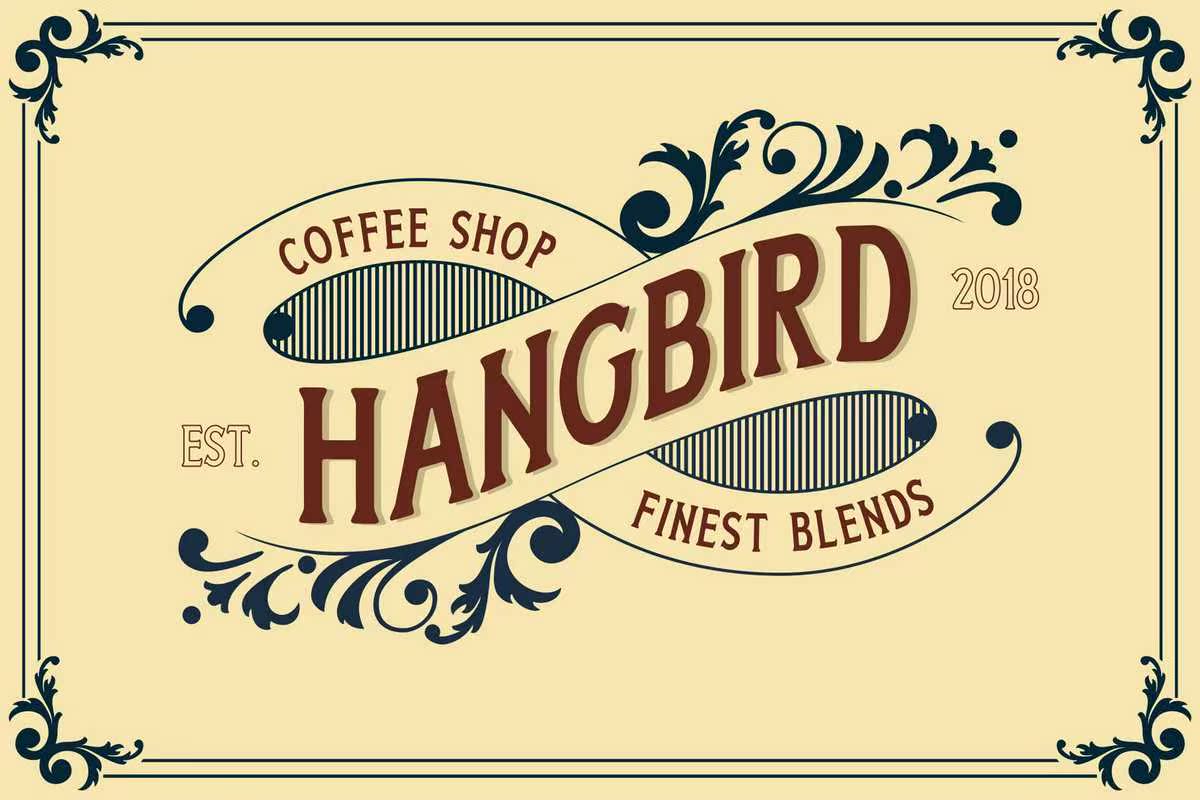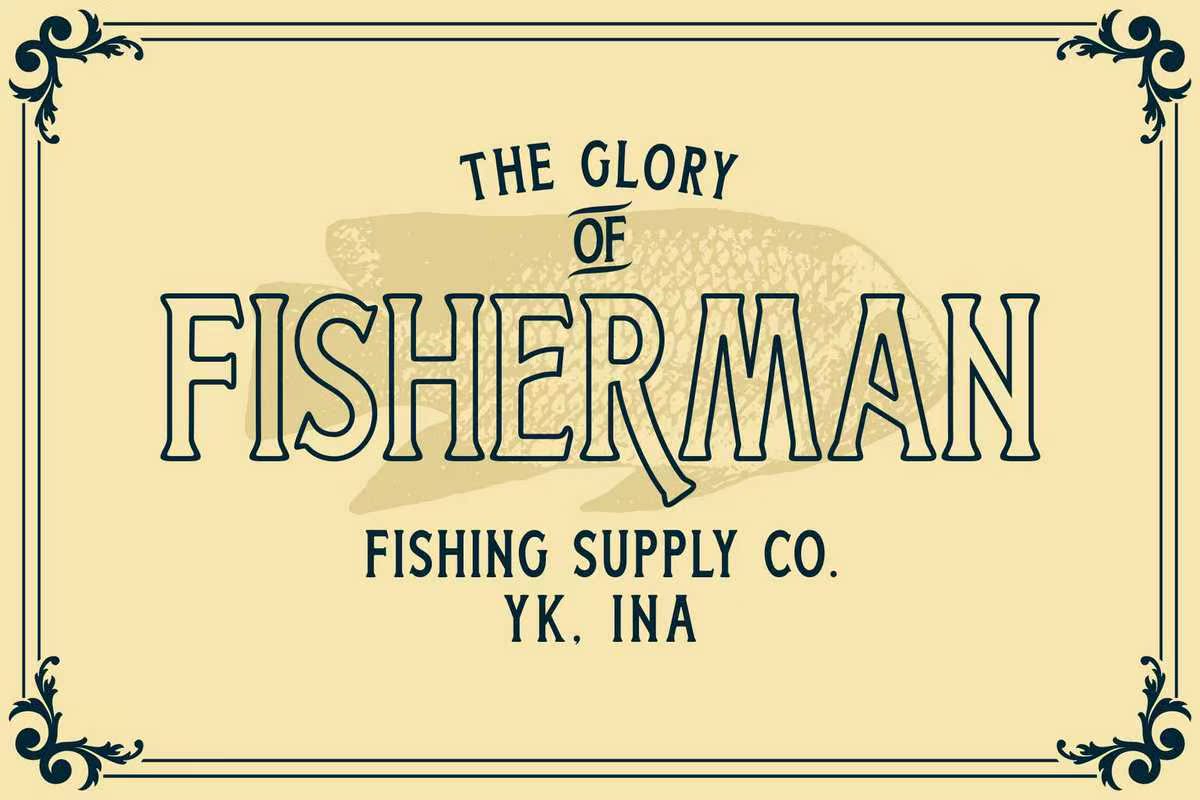
船夫是一个从经典的钥匙标签、商标和绘画中获得灵感的葡萄酒展示风格。船夫有三种风格(常规、轮廓和印记),可以扩展设计的可能性。船夫也有一种风格集,带有风格列表集,船工为您提供了多种选择,让您可以创造出自己想要的东西。混合并匹配其他字符,为您的设计添加吸引人的信息。船工是一种从经典的钥匙标签、标志和绘画中获得灵感的VintagedDisplayFont。船工有三种风格(常规,大纲和图章)扩展了您设计某物时的可能性。船夫也作为样式集。通过样式列表集,船夫为您提供了创建某物的选项。混合并匹配替换字符,以向您的设计添加吸引人的信息。